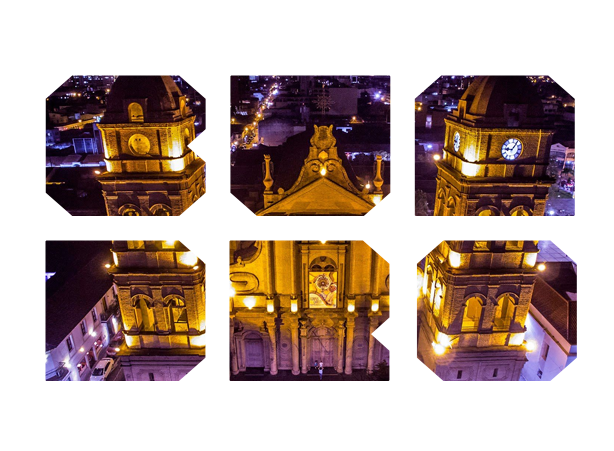
QDRD Display Font
Esta es una moderna fuente de fantasía basada en la modulación cuadrada. Se aplica fácilmente en carteles, y para textos cortos, trabaja muy bien como una pieza compositiva y combinada con imágenes logran excelentes resultados. Esta fuente ofrece una amplia variedad usos para ayudarlo a descubrir el mejor estado de ánimo para sus proyectos, desde carteles hasta títulos grandes. Con su aspecto poderoso, QDRD es perfecto para causar una fuerte impresión en medios impresos.